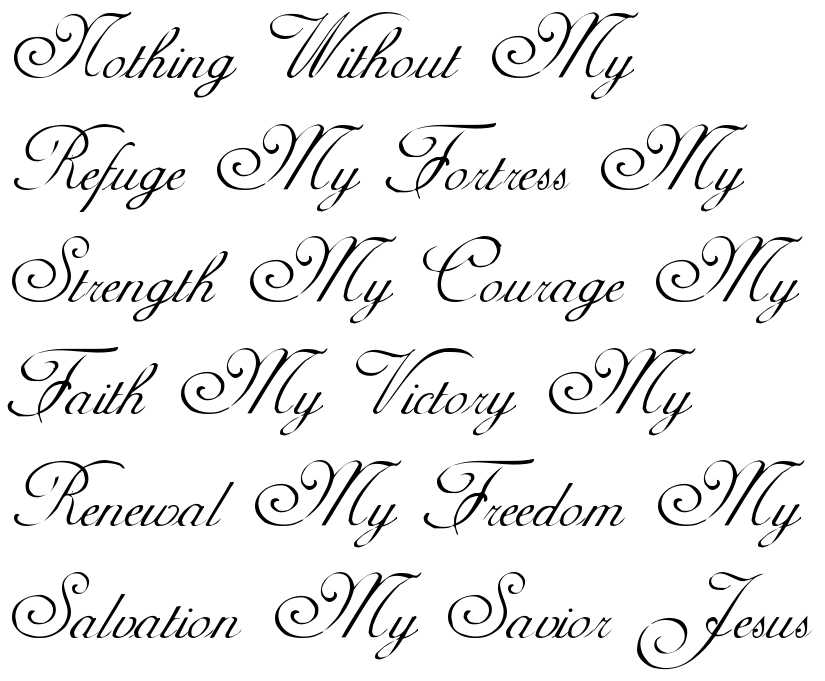
Какой стиль и размер шрифта взять для визитки? Выбор гарнитуры для визитки
Вопрос – какой шрифт лучше для визиток – почти всегда актуален как для заказчика, так и для исполнителя. С одной стороны, хочется выделиться на фоне окружающих, с другой – нельзя забывать об эстетике, легкости чтения и восприятия. Красивый шрифт для визитки – не только дань уважения к собеседнику, но и показатель вкуса владельца. Поэтому к этому вопросу нужно отнестись максимально ответственно. В этой статье мы расскажем о лучших гарнитурах и посоветуем, какой шрифт выбрать для визитки.
Какой должна быть солидная карточка
Визитные карточки давно и прочно вошли в нашу жизнь, поэтому сформировались четкие и понятные критерии качества. Поскольку типографское изделие, прежде всего, играет информативную роль, то данные должны легко читаться даже людьми с проблемным зрением. Поэтому минимальный размер шрифта на визитке печатается 10 кеглем. Больше 14 употреблять не стоит – это выглядит безвкусно.
Помимо дизайна, карточка с личными или корпоративными данными должна соответствовать и некоторым другим критериям.
- Чем качественнее бумага, тем лучше впечатление. Не нужно стремиться использовать дорогостоящие дизайнерские виды типа софт-тач, но плотная меловка или картон обязательны.
- Выигрышно выглядит дополнительная обработка изделий. Это может быть ламинация, конгрев, УФ-лакирование, вырубка, фольгирование, скругление уголков.
- Печать должна быть нанесена с одной стороны: оборот часто используется для записей. Двусторонние карточки допустимы только в случае английского и русского шрифта для визиток.
- Не стоит экспериментировать с нестандартными размерами. Типовые габариты 90*50 и 85*55 мм самые удобные.
- Черный текст на белом фоне – классика жанра. Не злоупотребляйте красками: карточка с 4 и более цветами смотрится аляповато и безвкусно.
- Не следует перегружать визитку информацией – это читается с трудом и выглядит нелепо.
Если у вас разные должности – закажите несколько видов изделий.
Гарнитура для визитки
Качество бумаги, цифровая печать, стойкие краски – это, безусловно, важно, но основное значение карточки заключается в том, чтобы рассказать собеседнику, кто вы, чем занимаетесь и как с вами связаться. Поэтому для имени и фамилии следует подбирать максимально простой и читаемый шрифт для визиток. Должность, телефоны, электронная почта печатается обычно на 2 размера меньше. Забудьте о рукописных, витиеватых, агрессивных шрифтах: начертание должно быть прямым и контрастным по отношению к фону. Существуют и другие правила оформления визитной карточки.
- Не стоит без необходимости употреблять курсив: он ухудшает восприятие и негативно сказывается на общем впечатлении.
- Жирным могут быть написаны только инициалы владельца. Дополнительные контактные данные делаются обычной гарнитурой.
- Следует избегать букв с засечками: прямые рубленые линии смотрятся более стильно и без труда читаются.
Оставьте любимый Times New Roman для листовок, флаеров и календарей. - Лучше всего употреблять знакомые начертания. Слишком узкие или широкие буквы, как и увеличенные или уменьшенные интервалы осложняют чтение.
- Ни в коем случае нельзя использовать на одной карточке более двух видов гарнитуры. Это существенно ухудшает восприятие и снижает имидж владельца.
- Также не рекомендуется слишком разбрасываться в габаритах текста. Оптимальный размер шрифта на визитке –
от 10 до 14 кегля.
Примеры хороших и плохих шрифтов для визиток
Лучшие шрифты для визиток
Творческие личности, возможно, будут против, но опыт показывает, что минимализм во всех его проявлениях с самой лучшей стороны характеризует обладателя такого качества. Это в полной мере относится и к дизайну полиграфии: можно изготовить карточки с многочисленными завитушками или даже придумать новое начертание, но вряд ли подобную концепцию одобрят серьезные деловые партнеры и простые клиенты, покупатели, заказчики, для которых информативность важнее всего.
- Arial
- Calibri
- Century Gothic
- Elephant
- Helvetica
- Microsoft Sans Serif
- Tahoma
- Verdana
Использование красивого и подходящего размера шрифта для визитки, использующего всю площадь, но не загромождающего поверхность, принесет немало дивидендов. Впечатление, произведенное с помощью бумажного прямоугольника, может вылиться в перспективное сотрудничество или выгодную сделку. Какой шрифт для визиток использовать в личных или корпоративных целях, подскажут дизайнеры нашей типографии. Предложим несколько вариантов, порекомендуем оптимальное решение. Разработка макета, печать и изготовление визитных карточек на современных цифровых машинах, послепечатные процессы выполняются в максимально сжатые сроки.
Шрифты для визиток как часть красивого дизайна
Способ подачи текстовой информации имеет огромное значение, когда речь идет о создании визитных карточек. Поэтому шрифты для визиток – часть дизайна, которая должна быть четко продумана. Далеко не всегда уместно экспериментировать с ними, подбирать витиеватые варианты, которые выглядят красиво, но могут затруднять читабельность текста промоматериалов.
11. Qanaya
Хотите, чтобы ваша визитная карточка выглядела элегантно? Шрифт Qanaya — это шрифт с засечками, доступный на Envato Elements и в других источниках с различной плотностью и размером шрифта.
12. Solomon
Еще один популярный шрифт с засечками для визитных карточек, доступный на Envato Elements.
Шрифт Solomon отличается креативным дизайном, который добавит изюминку обычной визитной карточке, сохраняя при этом ее элегантность и удобочитаемость.
13. Baskerville PT